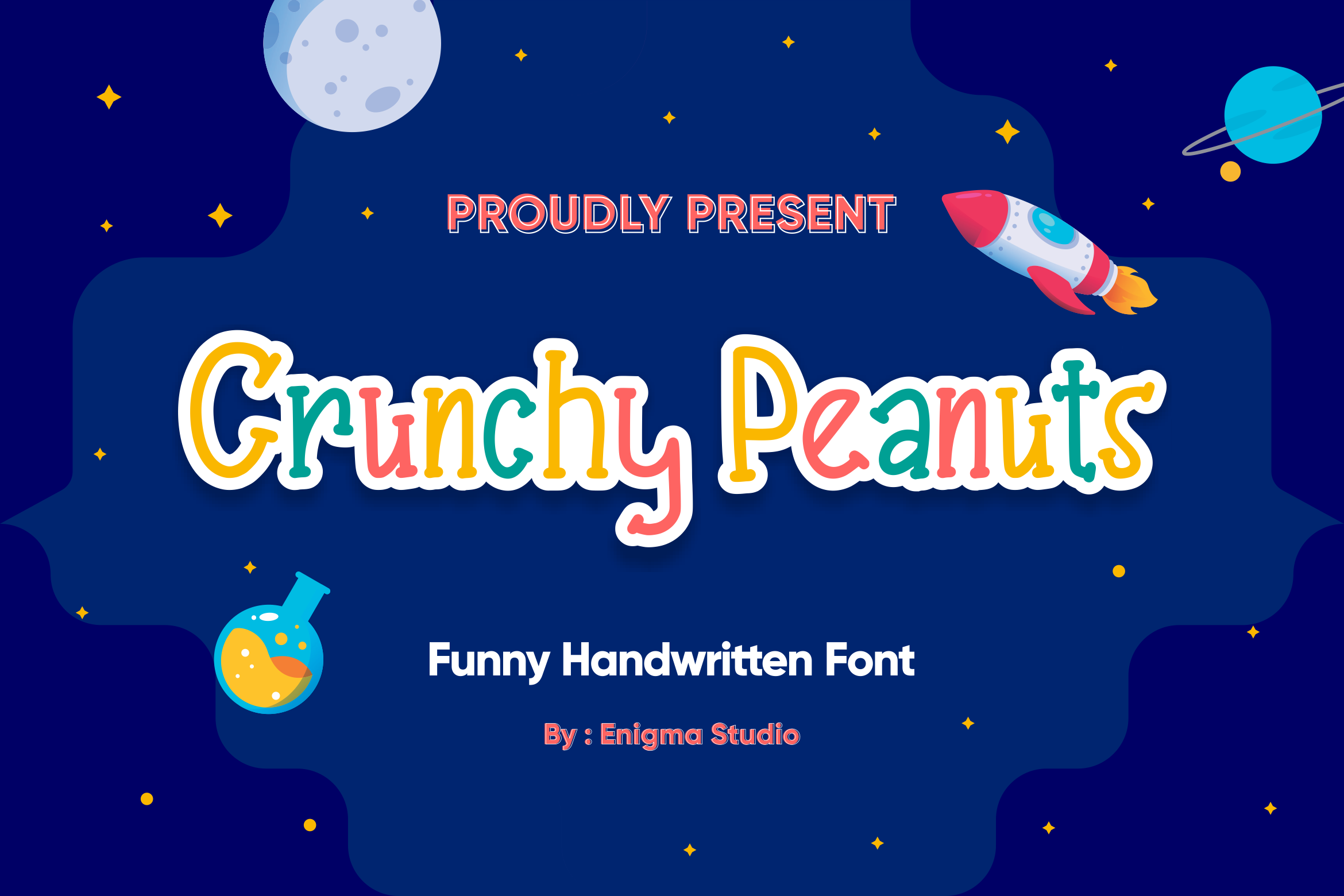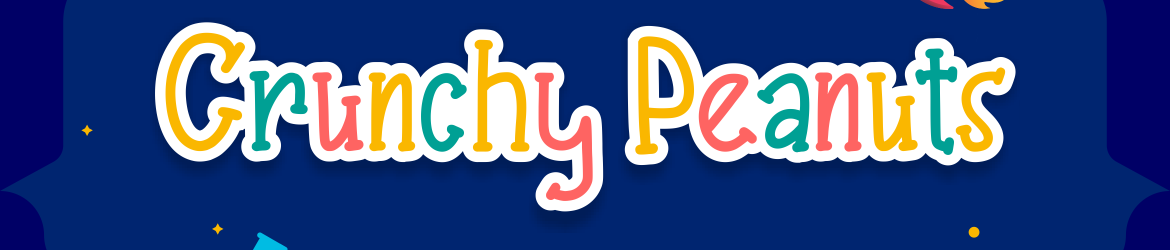
Crunchy Peanuts Font – Download Grátis
Esta é uma fonte escrita a mão com graça perfeita para diversas aplicações visuais. A fonte Crunchy Peanuts se destaca especialmente para produtos embalados, projetos de marca, revistas ou redes sociais. Ela também é perfeita para expressar mensagens acima do fundo em cartões-de-cabimento ou outros eventos especiais como casamentos. Para quem está buscando um estilo que seja ao mesmo tempo elegante e descontraído, essa fonte escrita a mão vai trazer uma atmosfera engraçada e vibrante. Ela não só vai dar um toque especial à sua identidade visual, mas também será capaz de expressar mensagens com personalidade, tornando-a uma escolha ideal para qualquer projeto onde você deseja destacar uma mensagem específica ou dar vida a imagens em seu design. Com sua textura fluida e cores vibrantes, a fonte Crunchy Peanuts é perfeita para criar um impacto visual imediato. É uma ótima opção tanto para elementos de marca quanto para designs gráficos que desejam transmitir uma mensagem divertida ou criativa. Esse design único vai trazer o seu projeto ao próximo nível, tornando-o chamativo e personalizado.